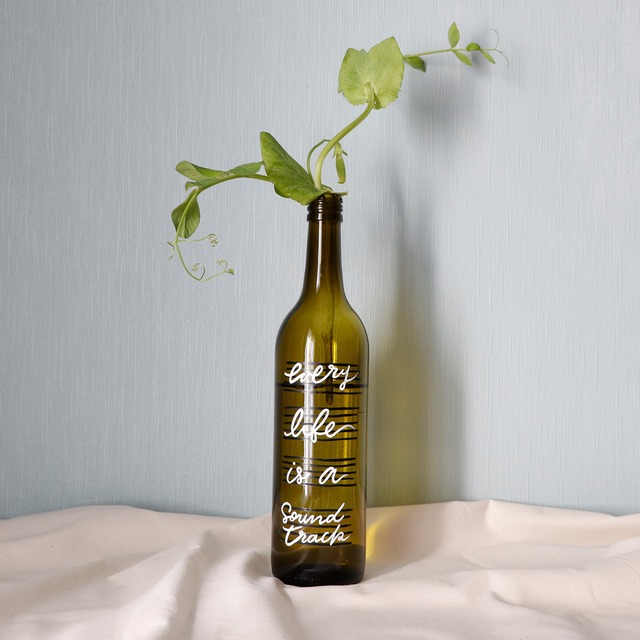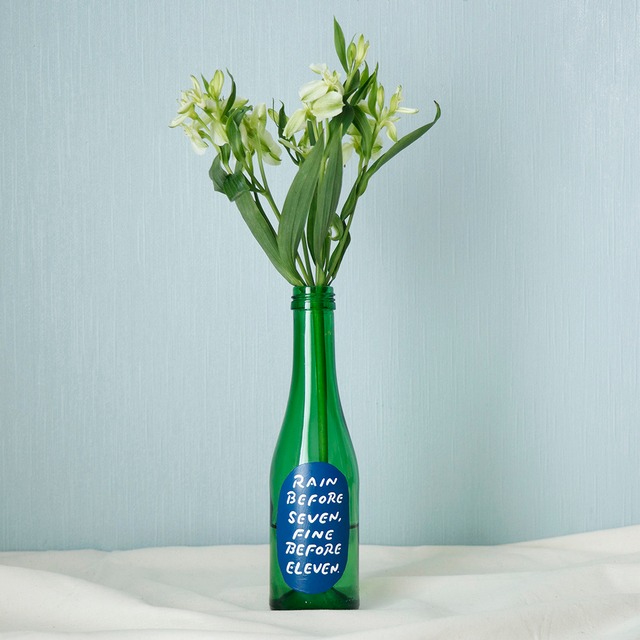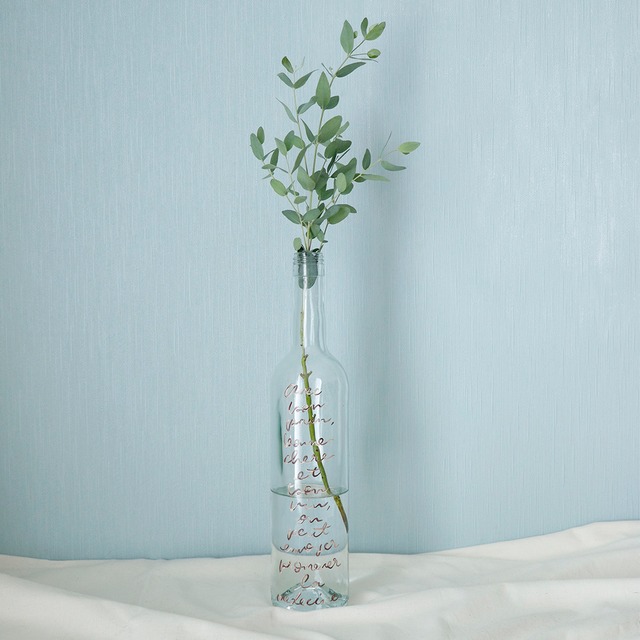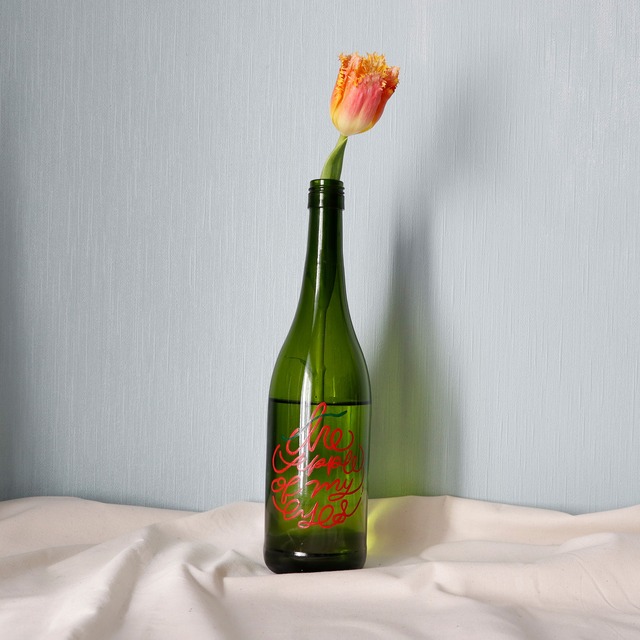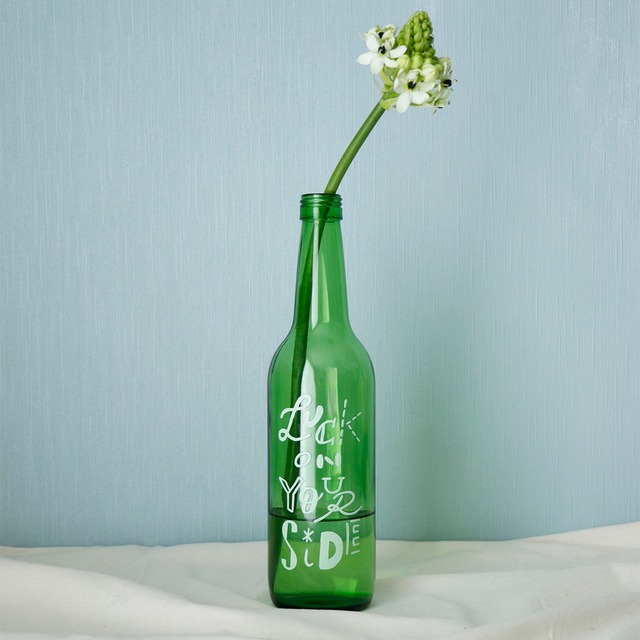
Habit is a second nature
Habit is a second nature 習慣は第二の天性なり 自分の話になりますが、毎朝日付と曜日を描いてSNSにアップする、という習慣があります。 気づけばもう11年半以上(?!)続けている朝の習慣です(2026年9月現在) 正直辞めどきが分からない感がありますが… それでも「続けている」ということが武器になっているのは事実。 そんな自分の気持ちをちょっとだけ込めた作品になっています。 ○サイズ:約227×158×20mm ◯重さ:約150g ○水性塗料使用 ○壁掛け用紐付(仮結びのため使用する場合はしっかりと結び直してください) ◯送料込み 【金額・送料について】 ¥10,000以上の商品のため送料が無料扱いとなっておりますが、大切な作品なので梱包をしっかりした状態でお届けしたいと考えております。 BASEでは、展示会やPOP UPなどで記載している金額に送料を追加した金額となっております。 対面で販売している時と金額が異なりますので、あらかじめご了承くださいませ。
He that falls today may rise tomorrow
He that falls today may rise tomorrow 直訳だと「今日倒れた人は明日は立ち上がるかもしれない」 日本語のことわざに当てはめるなら「七転び八起き」 フレーズ自体には「8」は入っていませんが、 七転び八起きから取って数字の「8」をモチーフにしています。 今日よりも明日、転んだら起き上がりたい。 へこたれそうな時にオススメの作品です。 ○サイズ:約270×220×20mm ◯重さ:約180g ○水性塗料使用 ○壁掛け用紐付(仮結びのため使用する場合はしっかりと結び直してください) ◯送料込み 【金額・送料について】 ¥10,000以上の商品のため送料が無料扱いとなっておりますが、大切な作品なので梱包をしっかりした状態でお届けしたいと考えております。 BASEでは、展示会やPOP UPなどで記載している金額に送料を追加した金額となっております。 対面で販売している時と金額が異なりますので、あらかじめご了承くださいませ。
NO BOOK NO LIFE
NO BOOK NO LIFE 本なしでは生きられない! よく見ると全部「本」のフォントになっています。 こういう方、たくさんいらっしゃるのでは?と思いながら描きました。 本好きの方へのプレゼントにも良いですね◎ ○サイズ:約270×190×20mm ◯重さ:約180g ○水性塗料使用 ○壁掛け用紐付(仮結びのため使用する場合はしっかりと結び直してください) ◯送料込み 【金額・送料について】 ¥10,000以上の商品のため送料が無料扱いとなっておりますが、大切な作品なので梱包をしっかりした状態でお届けしたいと考えております。 BASEでは、展示会やPOP UPなどで記載している金額に送料を追加した金額となっております。 対面で販売している時と金額が異なりますので、あらかじめご了承くださいませ。
Rain before seven, fine before eleven
Rain before seven, fine before eleven 7 時前の雨は11 時前に上がる イギリスの天気にまつわることわざから。 最初は上手くいかなくてもだんだんと好転する、というフレーズです。 雨と雲と雨が止んだ後の空、水たまりをイメージしたカラーにしました。 ○サイズ:約270×220×20mm ◯重さ:約180g ○水性塗料使用 ○壁掛け用紐付(仮結びのため使用する場合はしっかりと結び直してください) ◯送料込み 【金額・送料について】 ¥10,000以上の商品のため送料が無料扱いとなっておりますが、大切な作品なので梱包をしっかりした状態でお届けしたいと考えております。 BASEでは、展示会やPOP UPなどで記載している金額に送料を追加した金額となっております。 対面で販売している時と金額が異なりますので、あらかじめご了承くださいませ。
Laughter is the best medicine
Laughter is the best medicine 笑いは最良の薬 グダグダ悩んでいても、友人や家族と笑って話しているとスッキリすることありますよね。 笑うって大切!心のお薬! カプセルのイラストにそんなフレーズを詰め込みました。 ○サイズ:約270×220×20mm ◯重さ:約180g ○水性塗料使用 ○壁掛け用紐付(仮結びのため使用する場合はしっかりと結び直してください) ◯送料込み 【金額・送料について】 ¥10,000以上の商品のため送料が無料扱いとなっておりますが、大切な作品なので梱包をしっかりした状態でお届けしたいと考えております。 BASEでは、展示会やPOP UPなどで記載している金額に送料を追加した金額となっております。 対面で販売している時と金額が異なりますので、あらかじめご了承くださいませ。
HAPPY of the world
HAPPY! いろんな国の言葉で、「うれしい」 知っている「うれしい」はいくつありますか? 円形のキャンバスなので、飾り方いろいろ! ○サイズ:約Φ250mm、厚み20mm ◯重さ:約200g ○水性塗料使用 ○壁掛け用紐付(仮結びのため使用する場合はしっかりと結び直してください) ◯送料込み 【金額・送料について】 ¥10,000以上の商品のため送料が無料扱いとなっておりますが、大切な作品なので梱包をしっかりした状態でお届けしたいと考えております。 BASEでは、展示会やPOP UPなどで記載している金額に送料を追加した金額となっております。 対面で販売している時と金額が異なりますので、あらかじめご了承くださいませ。
The flower that blooms in adversity is the rarest and most beautiful of all
The flower that blooms in adversity is the rarest and most beautiful of all 逆境の中で咲く花は、どの花よりも貴重で美しい 世の中にはいろんな花があるように、 それぞれがたくましく自由に咲いているイメージで描きました。 文字の色は花の色、葉っぱの色を表現しています。 キャンバスをはみ出すくらい、のびのびと咲き誇りましょう◎ ○サイズ:約333×220×20mm ◯重さ:約200g ○水性塗料使用 ○壁掛け用紐付(仮結びのため使用する場合はしっかりと結び直してください) ◯送料込み 【金額・送料について】 ¥10,000以上の商品のため送料が無料扱いとなっておりますが、大切な作品なので梱包をしっかりした状態でお届けしたいと考えております。 BASEでは、展示会やPOP UPなどで記載している金額に送料を追加した金額となっております。 対面で販売している時と金額が異なりますので、あらかじめご了承くださいませ。
There is always light behind the clouds
There is always light behind the clouds 一番大好きなフレーズ! 好きすぎてアクリルキーホルダーやボトルにも描いています。 (ちなみにスマホの待受もこれです) 青空に雲が浮かんでいて、水滴が光っているイメージ。 その場がパッと明るくなるように描きました。 ○サイズ:約530×410×20mm ◯重さ:約480g ○水性塗料使用 ○壁掛け用紐付(仮結びのため使用する場合はしっかりと結び直してください) ◯送料込み 【金額・送料について】 ¥10,000以上の商品のため送料が無料扱いとなっておりますが、大切な作品なので梱包をしっかりした状態でお届けしたいと考えております。 BASEでは、展示会やPOP UPなどで記載している金額に送料を追加した金額となっております。 対面で販売している時と金額が異なりますので、あらかじめご了承くださいませ。
favorite phrase2(シルクスクリーン)
favorite phrase2 2026年4月に開催した個展「favorite phrase2」のメインビジュアルを キャンバスにシルクスクリーン印刷した作品です。 全フォント、音楽と楽譜をモチーフにしたものになっています。 音楽やってる方、ぜひ答え合わせしてみてください♪ 同じデザインのトートバッグ、ステッカーもございます。 【トートバッグ】 https://tomomitype.thebase.in/items/150293752 【ステッカー】 https://tomomitype.thebase.in/items/150299400 ○サイズ:約333×220×20mm ◯重さ:約200g ○壁掛け用紐付(仮結びのため使用する場合はしっかりと結び直してください) ◯送料込み 【金額・送料について】 ¥10,000以上の商品のため送料が無料扱いとなっておりますが、大切な作品なので梱包をしっかりした状態でお届けしたいと考えております。 BASEでは、展示会やPOP UPなどで記載している金額に送料を追加した金額となっております。 対面で販売している時と金額が異なりますので、あらかじめご了承くださいませ。
words flower 018 / favorite phrase2
words flower 018 favorite phrase2 2026年4月に開催した個展「favorite phrase2」のメインビジュアルで描いた文字の花です。 モデルの花はアイスランドポピー。 どっしりとした花とクネクネした茎、咲くのか咲かないのかドキドキな蕾(咲きませんでした)を 「favorite phrase」の文字に載せています。 お花を飾るように、お部屋の壁に飾ってくださいね◎ ○サイズ:約455×380×20mm ◯重さ:約380g ○水性塗料使用 ○壁掛け用紐付(仮結びのため使用する場合はしっかりと結び直してください) ◯送料込み 【金額・送料について】 ¥10,000以上の商品のため送料が無料扱いとなっておりますが、大切な作品なので梱包をしっかりした状態でお届けしたいと考えております。 BASEでは、展示会やPOP UPなどで記載している金額に送料を追加した金額となっております。 対面で販売している時と金額が異なりますので、あらかじめご了承くださいませ。
words flower 019/pride
words flower 019 アマリリスの花言葉「誇り/pride」 凛とした佇まいのアマリリス。 お水も土もいらない、球根から成長を見守れる「マジックアマリリス」を育ててみたら 少しずつスラッとした葉っぱと茎が伸びて、一気に大輪の花を咲かせました。(しかも2回!!) この姿を絵に残しておきたくて描いた1枚です。 お花を飾るように、お部屋の壁に飾ってくださいね◎ ○サイズ:約410×318×20mm ◯重さ:約300g ○水性塗料使用 ○壁掛け用紐付(仮結びのため使用する場合はしっかりと結び直してください) ◯送料込み 【金額・送料について】 ¥10,000以上の商品のため送料が無料扱いとなっておりますが、大切な作品なので梱包をしっかりした状態でお届けしたいと考えております。 BASEでは、展示会やPOP UPなどで記載している金額に送料を追加した金額となっております。 対面で販売している時と金額が異なりますので、あらかじめご了承くださいませ。
【BOTTLE PAINT ART】every life has a soundtrack
every life has a soundtrack 全ての人生にはサウンドトラックがある 五線譜に文字が乗っています♪ 楽譜っぽく、白と黒で描いてるのでグリーンなお花が似合うかも? 花瓶として、そのまま飾ってディスプレイとしても◎(食用はおすすめしません) 光が入るとこに置くと、瓶の色とともに文字も影になって素敵ですよ!! 空き瓶に文字を直接ペイントしています。クリアコーティングしていますが、引っ掻きに弱いので取扱いの際はご注意ください。 ◯サイズ 高さ305mm、直径Φ70mm ◯重さ 約380g ※若干の誤差はご了承ください。 ※画像はイメージです。お花はつきません。